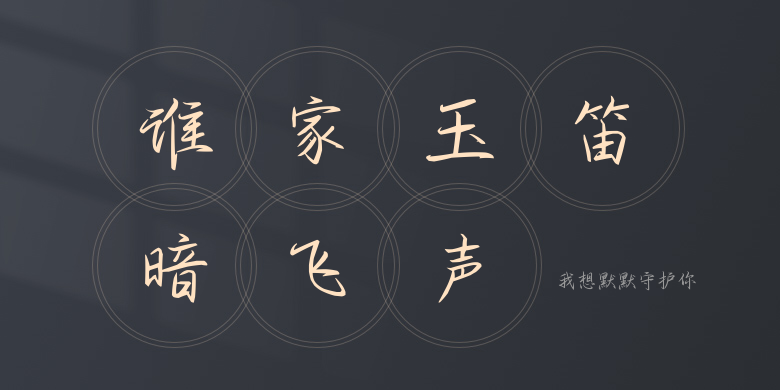
我想默默守护你
我想默默守护你,这款字体结构工整、笔画清晰,兼顾美观与易读性,适用于标题、正文、海报、包装、LOGO 等多种场景。字形优雅稳定,风格百搭耐看,适配日常排版与创意设计,让文字呈现更舒适、更具质感。我想默默守护你一笔一画,皆是细节,以均衡的比例、流畅的线条打造舒适视觉体验,字形端正大气,风格简约现代。无论是商业设计、品牌宣传还是日常排版,都能轻松驾驭,让文字更有格调与力量。我想默默守护你字体下载。